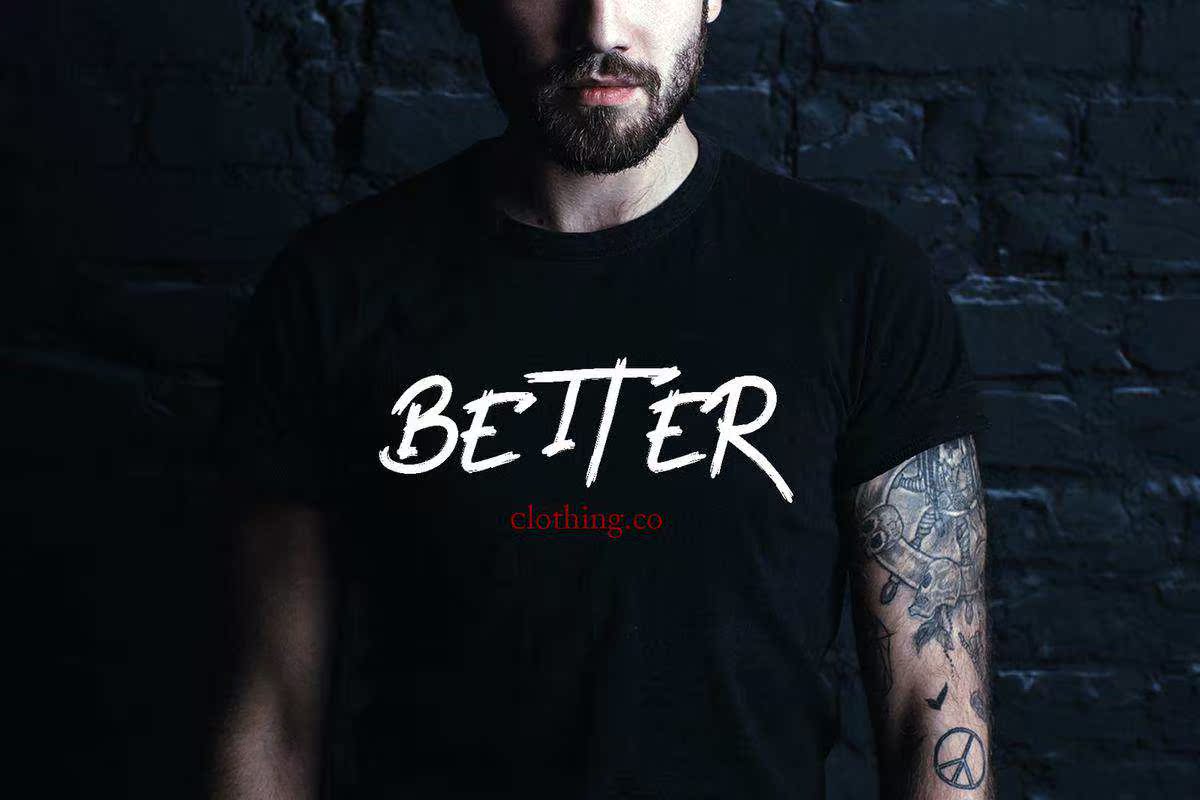
BlackMantais Astrong Characterized,Brushed Display Font.It looks viouse and Urban and It willy’s肯定会让你的每一个设计都脱颖而出。添加你最喜欢的创意,让你的自我与生成的一样闪耀。BlackMantais Astrong Characterized,刷式显示字体。它的颜色强烈且城市化,几乎肯定会让您的每一项设计都脱颖而出。添加您最喜欢的创意,让您自己在生成的所有创意中闪耀。